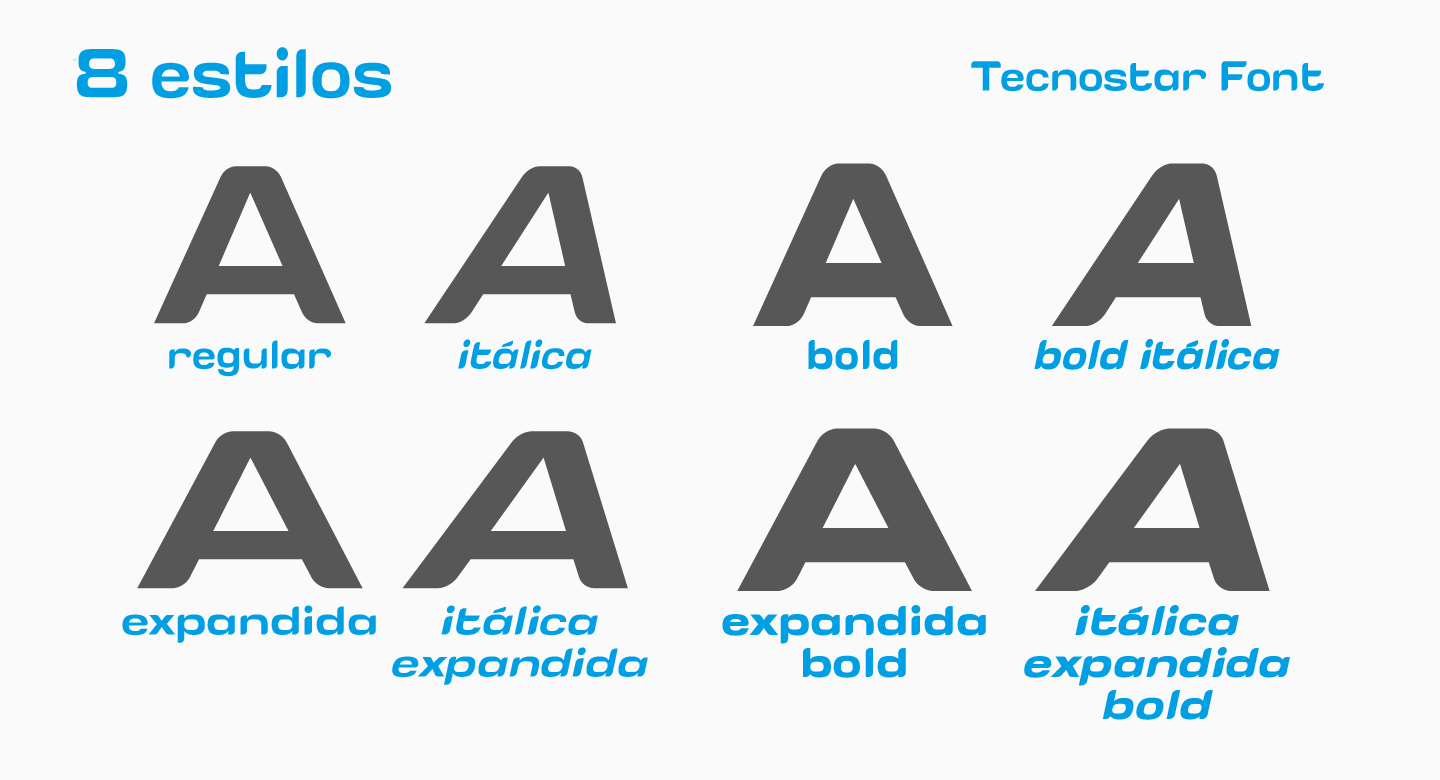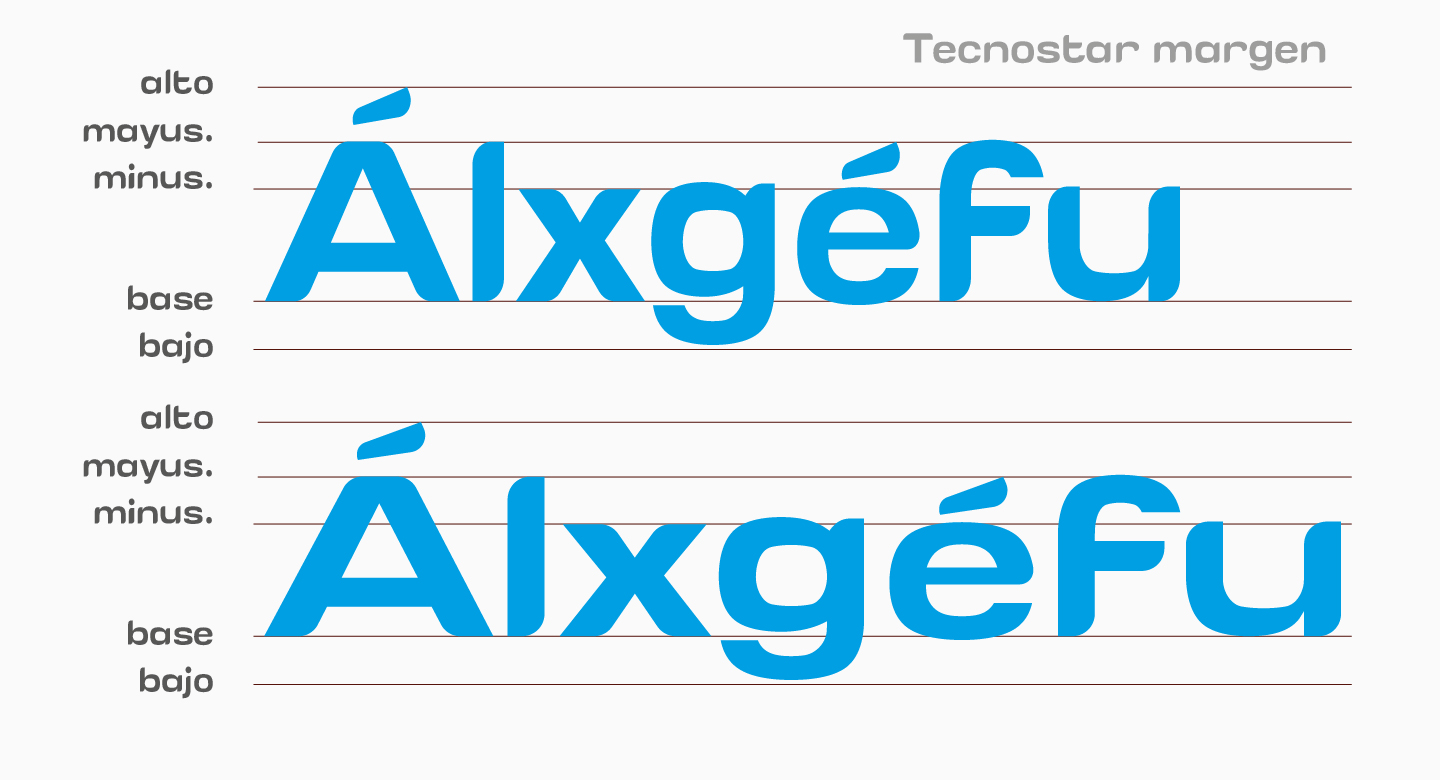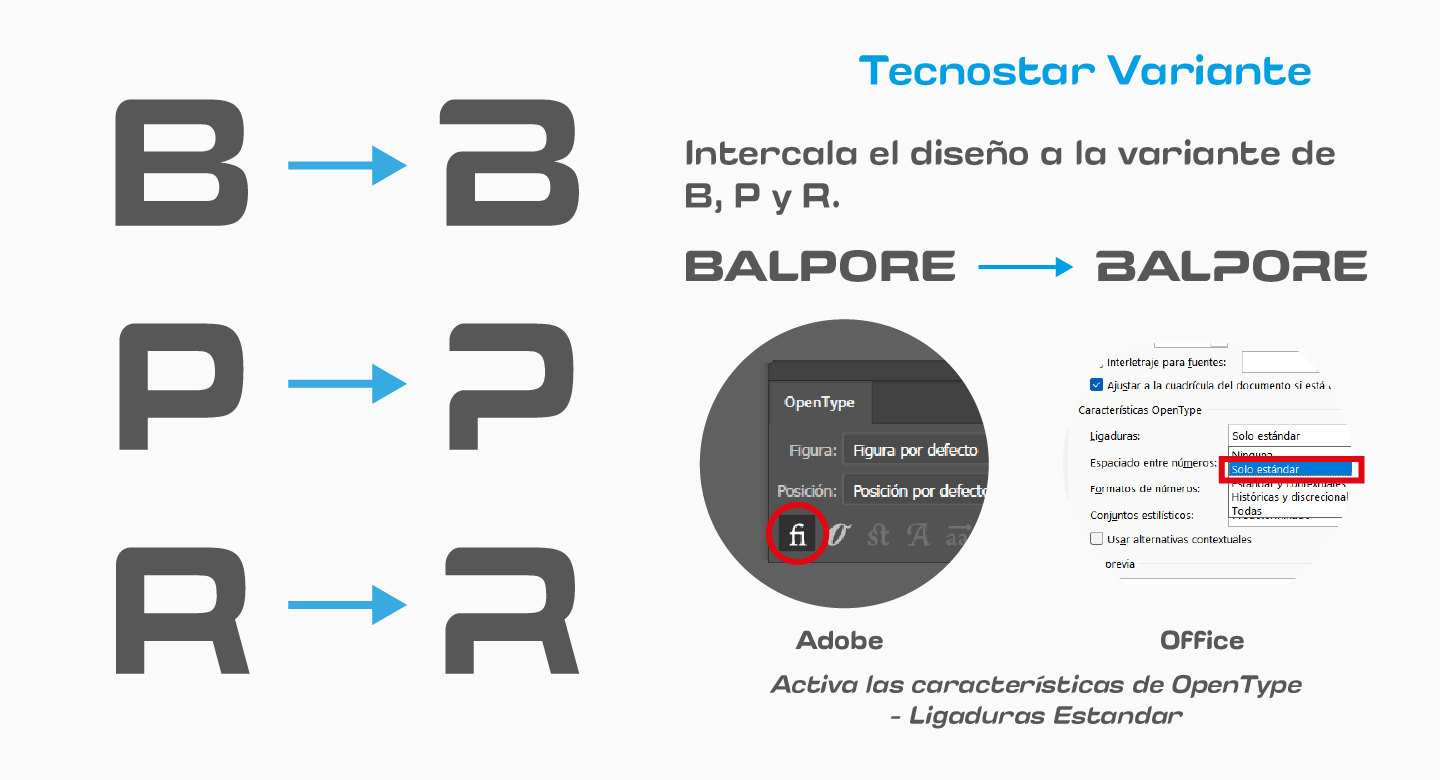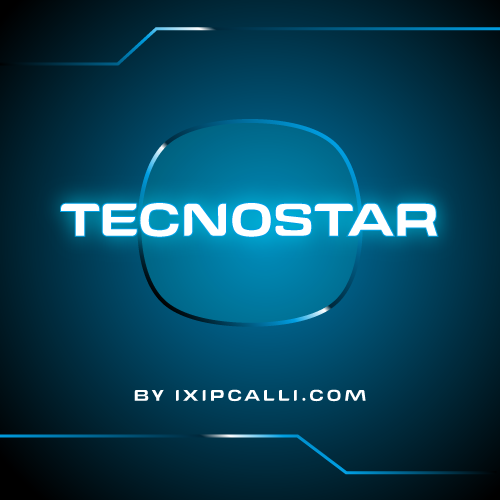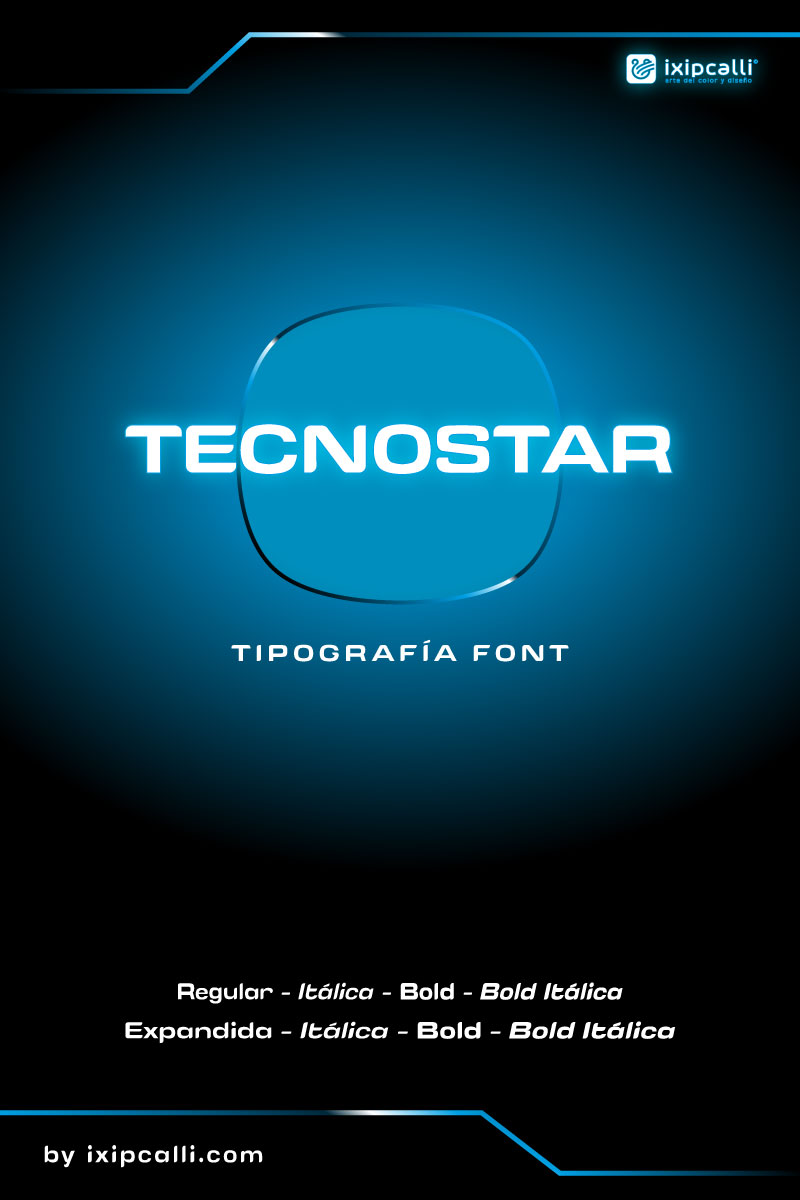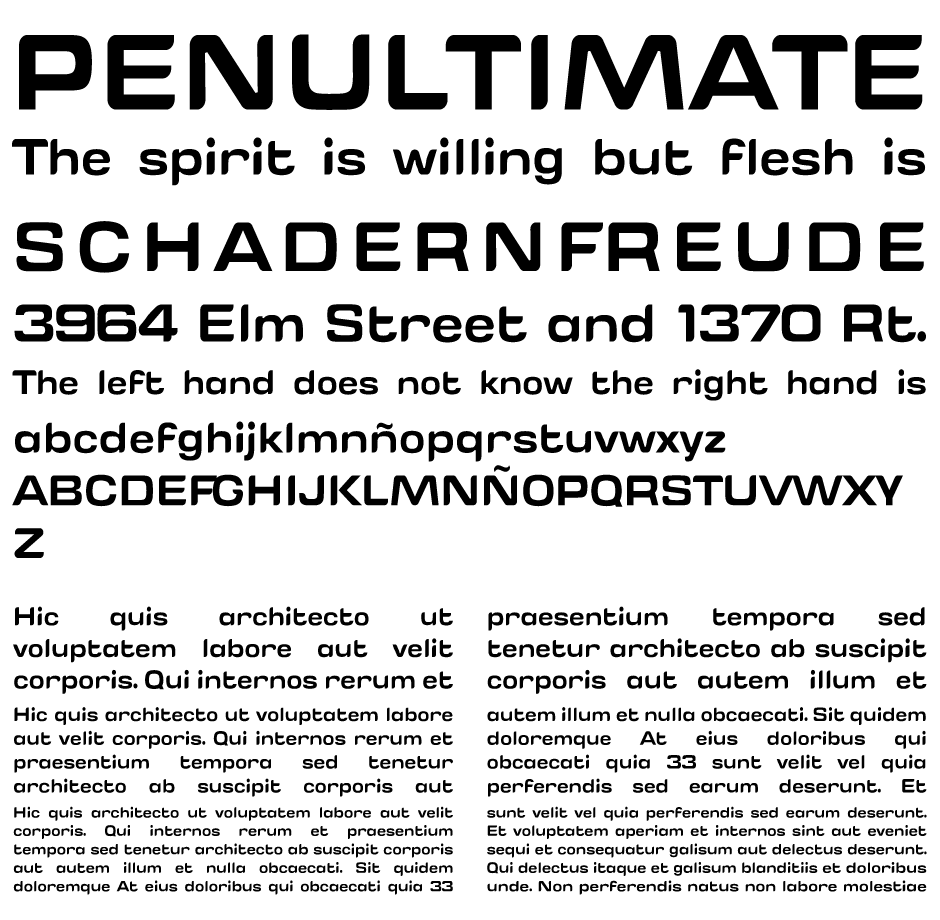
tecnostar
Descripción
(2026) - Tecnostar está diseñada para destacar en títulos, logotipos y piezas visuales de alto impacto, especialmente en proyectos relacionados con gaming, tecnología, electrónica o branding moderno. Su personalidad visual combina precisión técnica con un carácter experimental, generando una sensación de movimiento y avance hacia el futuro.
Su diseño es ideal para proyectos de branding tecnológico, posters, portadas, interfaces digitales que buscan una identidad vanguardista. Su estilo futurista, geométrico y cortes segmentados, evocan interfaces digitales y estética sci-fi. Cuenta con dos pesos (regular y extendida), además de sus formas itálicas y negritas por peso.
Esta tipografía fue diseñada para un proyecto de robots inteligentes, por lo que cuenta cos tres letras modificadas, B, P y R que pueden ser usadas y evocar el nombre de la marca.